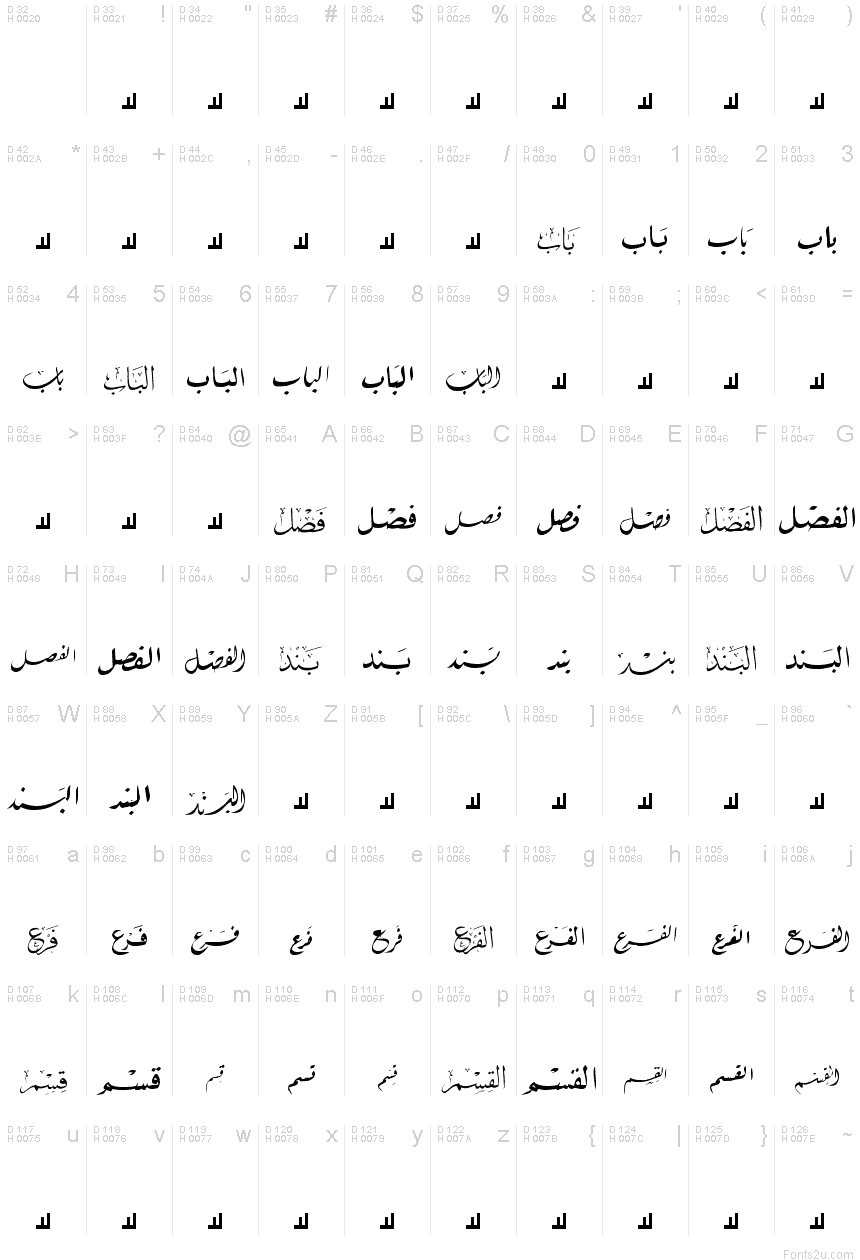
Mcs Book Title 1 هو خط عربي مجاني للعناوين يتميز بإيقاع خطي انسيابي. تتحرك الحروف بمنحنيات عريضة ومنخفضة مع لمسات حادة ومقطوعة، مما يضفي على الخط طابعاً أدبياً وتصميمياً يوحي بالرسمية مع الحفاظ على الانسيابية.
يتناسب الخط مع أغلفة الكتب، وعناوين المجلات، والملصقات الثقافية، وافتتاحيات الفصول، وبطاقات العناوين حيث يساهم الامتداد الأفقي الطويل في إثراء التكوين البصري. باعتباره خطاً مجانياً، فهو مثالي للاستخدام في العناوين القصيرة، خاصة في أغلفة الكتب والترويسات التحريرية، حيث تخلق القوائم الرأسية العالية والوصلات الممتدة خطاً قوياً وبارزاً عبر الصفحة.